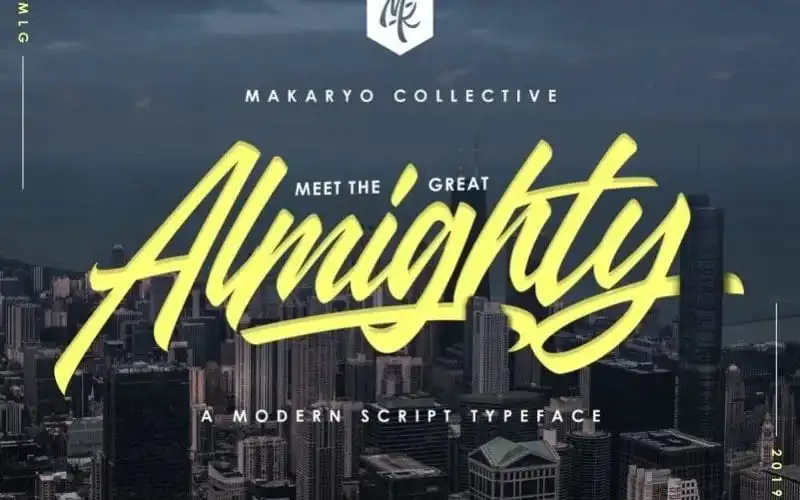
Esta fonte chamada ‘Almighty Script’ é perfeita para designers que buscam inovação em seus projetos. Ela inclui muitas alternativas para cada letra minúscula, permitindo transformar palavras de maneira divertida e personalizada. Os tipos de letras criados pelo Makaryo Collective são ideais tanto para logotipos quanto para textos menores e materiais impressos. Com sua versão maiuscula, minúscula, números e símbolos comuns inclusos, esta fonte é um recurso valioso para qualquer designer. Além disso, o ‘Almighty Script’ oferece alternativas, ligaturas e cunhas, dando-lhe flexibilidade de uso em uma ampla gama de projetos. Perfeito para designers que procuram criatividade e personalização nos seus trabalhos gráficos, esta fonte é um recurso indispensável. Suas opções completas oferecem a possibilidade de transformar qualquer palavra em algo único e personalizado, tornando o design mais interessante e diversificado.